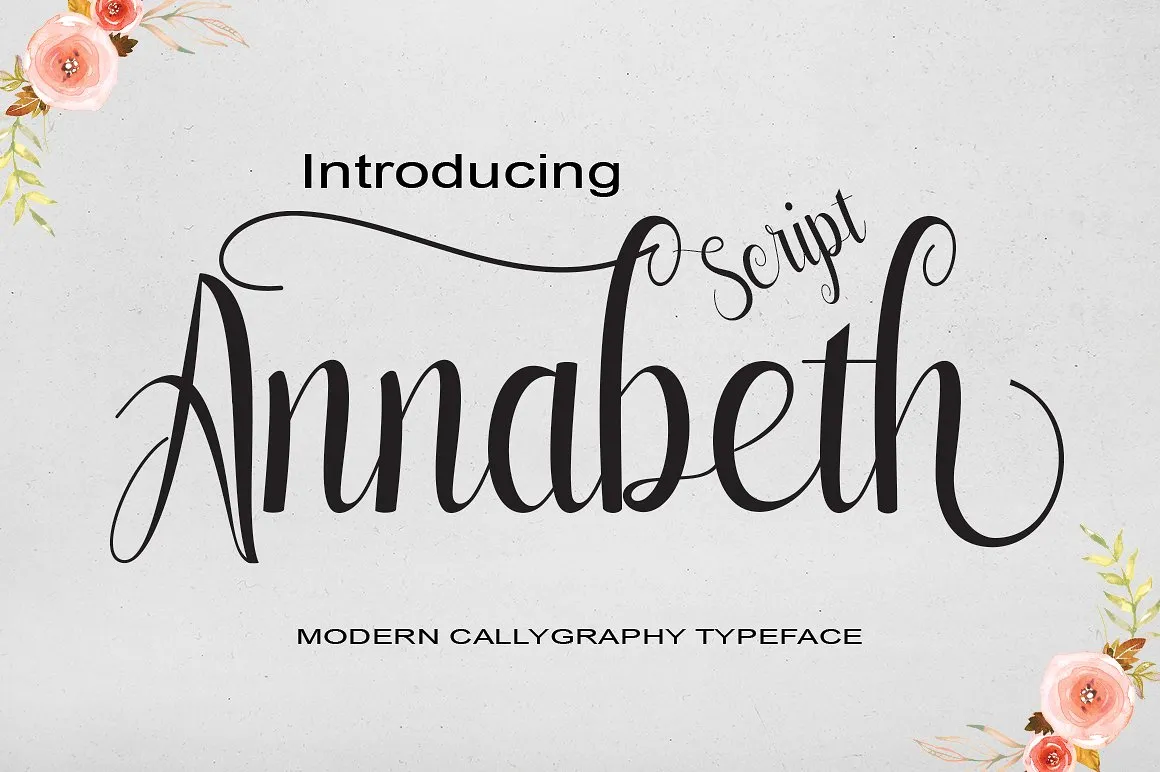
Annabeth Script Font – Fonte Grátis
Annabeth Script Font
A Annabeth Script Font oferece uma experiência única para os designadores digitais brasileiros. Introduzida pela Befonts, essa elegante fónta é resultado do trabalho criativo de StudioRz. A Annabeth traz formas modernas e únicas da escrita contínua, com um estilo que evoca a natureza. Ela não é apenas uma fonte, mas uma adição encantadora ao seu arsenal de recursos gráficos. Com seu próprio estilo chamativo, a Annabeth se adequa perfeitamente às criações modernas e inspiradoras do design. Seria um prazer adicioná-la à sua coleção para enriquecer ainda mais o trabalho do designer brasileiro.